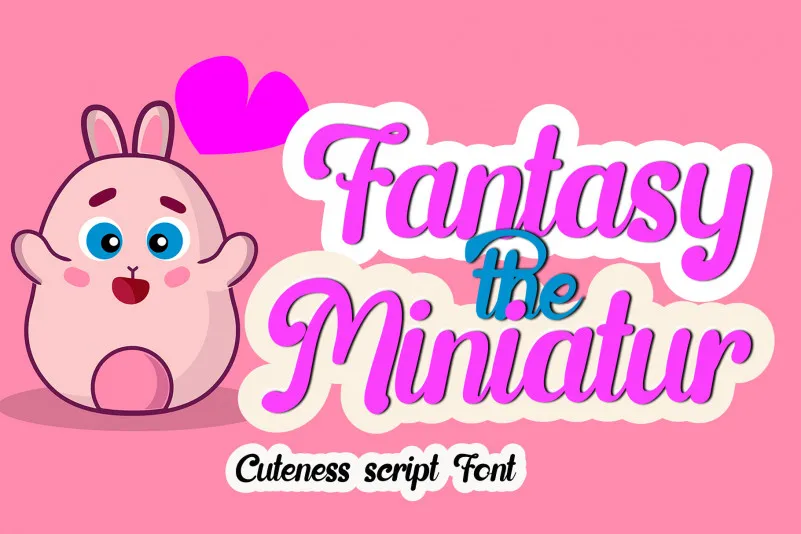
A Fantasy The Miniatur é uma fonte script retratada como uma tipografia relaxada e descontraída, ideal para quem procura algo além do estático no seu dia a dia. Esta font oferece um estilo encantador que se destaca por sua versatilidade em diversos tipos de conteúdo — seja ele editorial, digital ou até mesmo gráficos 3D. Ideal para aqueles que buscam uma adição única e divertida à biblioteca de fontes do seu projeto, a Fantasy The Miniatur é capaz de tornar qualquer criação especial. Seja ela um design de papel, um layout digital, ou até mesmo um graphic arte, esta font é um elemento chave que eleva suas produções para o próximo nível. Inspirada no estilo das escritas manuscritas dos séculos antigos, a Fantasy The Miniatur oferece uma aparente leveza e elegância, fazendo com que sua presença seja inegável em qualquer projeto onde se encontre. Para aqueles buscando algo diferente, esta font é um ótimo adicional para seus recursos gráficos, combinando charme com funcionalidade.